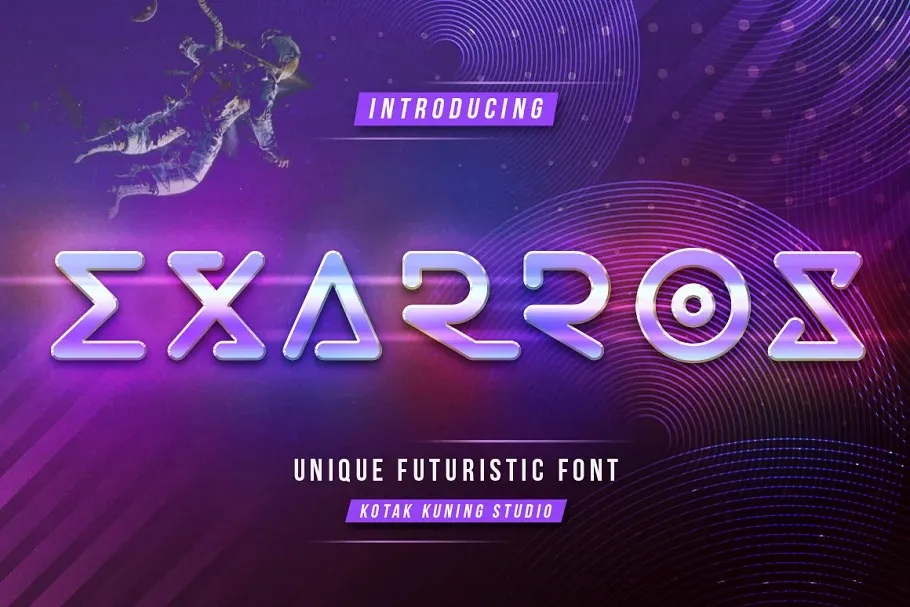
Exarros Font
Esta é uma família de fontes futurísticas que apresenta caracteres maiúsculos com um conjunto de números que exibem um design único e futurista, além de alternativas galáxicamente criativas. A Exarros Font não apenas oferece alegria ao olhar para sua aparência moderna e inovadora, mas também impulsiona o design em direção à tecnologia e aos desafios do futuro. É perfeita para ambientes digitais que procuram uma fonte com um toque de fantasia espacial para estilizar seus materiais de texto ou criar a sensação de estar navegando pelo cosmos digital. Com Exarros Font, seu projeto ganha vida e se transforma em algo excepcionalmente moderno e excitante.